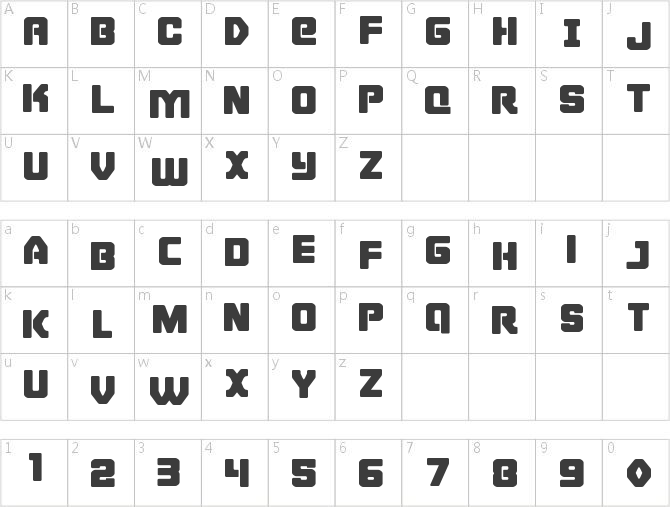
Cyborg Rooster Expanded 詳情頁
Cyborg Rooster Expanded字體字庫是一款讓人賞心悅目、百看不厭的英文字體,適合各類廣告和產(chǎn)品包裝設(shè)計(jì)應(yīng)用,字體大小0.04MB,格式為ttf字體,上傳用戶是373790005,作者/版權(quán)方為未知